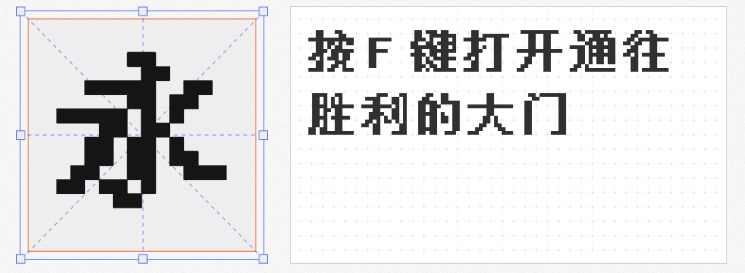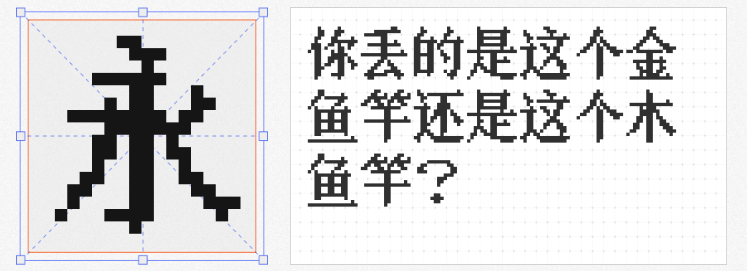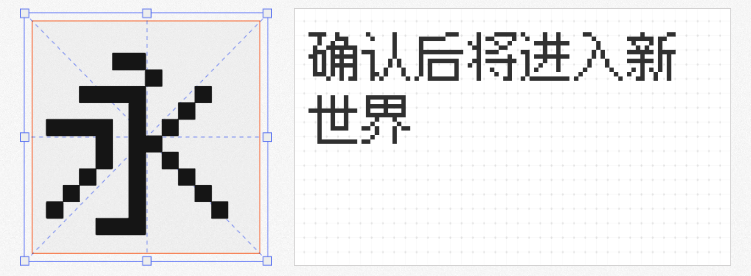
在游戏设计的广阔天地里,像素风格以其独特的复古魅力与怀旧情怀,持续吸引着无数玩家的目光。而像素字体,作为这一风格不可或缺的元素,更是为游戏世界增添了别样的韵味。今日,就为大家推荐四款适用于游戏设计的免费商用像素字体,让你的游戏界面焕发别样光彩。
1. 粗柳坊新16x Bold
作为ChuLyu字体的升级替代品,这款宋体像素字体以其鲜明的笔画粗细变化脱颖而出。在16x16的像素格内,它巧妙地运用了对比,使得每一个字符都显得生动而灵敏,为游戏界面注入了一股活泼的气息。
作为一款开源的泛中日韩像素字体,它以黑体无衬线风格呈现,简洁明了。支持10、12和16像素多种规格,无论是细腻的游戏文本还是醒目的标题,都能轻松驾驭,是游戏开发者们的得力助手。
3. 天王星像素
基于文泉驿点阵中文字库的这款点阵字体,以其不粘连的粗体特色著称。在游戏设计中,清晰的字符显示至关重要,天王星像素字体正是凭借这一优势,确保了玩家在游戏过程中能够轻松阅读,不受字体模糊之扰。
4. 甜橙点阵体
这款7像素点阵字体,以其超乎寻常的清晰度赢得了众多设计者的青睐。相较于同类型字体,甜橙点阵体在细节处理上更为出色,无论是游戏界面还是软件界面,都能展现出其独特的清晰美感,为玩家带来更加舒适的游戏体验。
这四款像素字体,各具特色,均为免费商用,无论是复古风格的游戏,还是现代简约的设计,都能找到适合你的那一款。